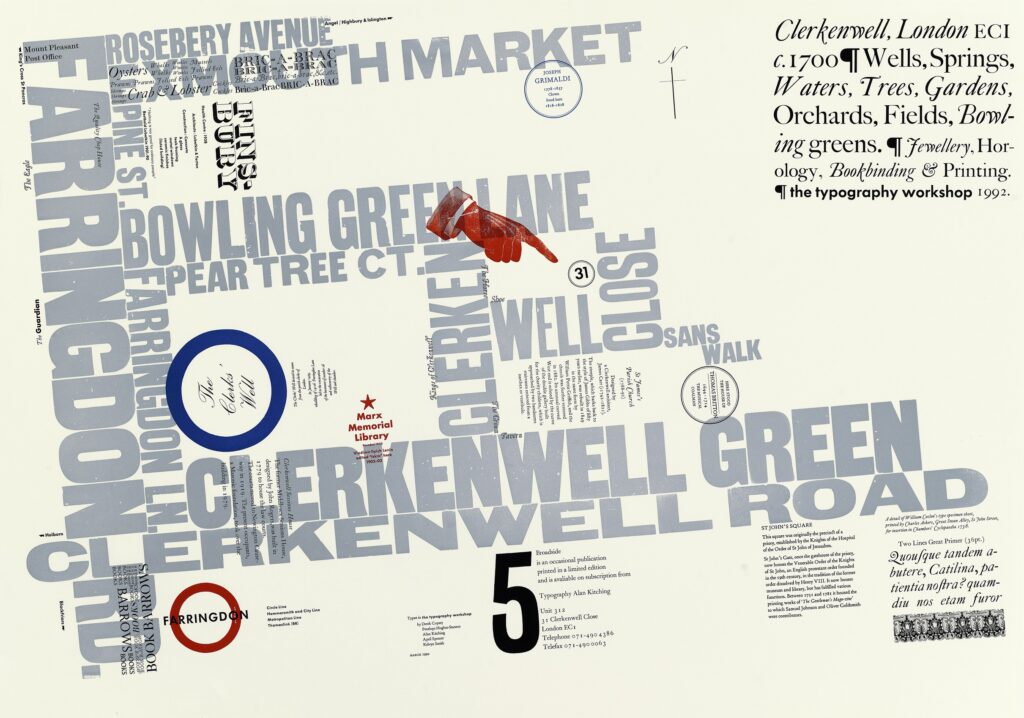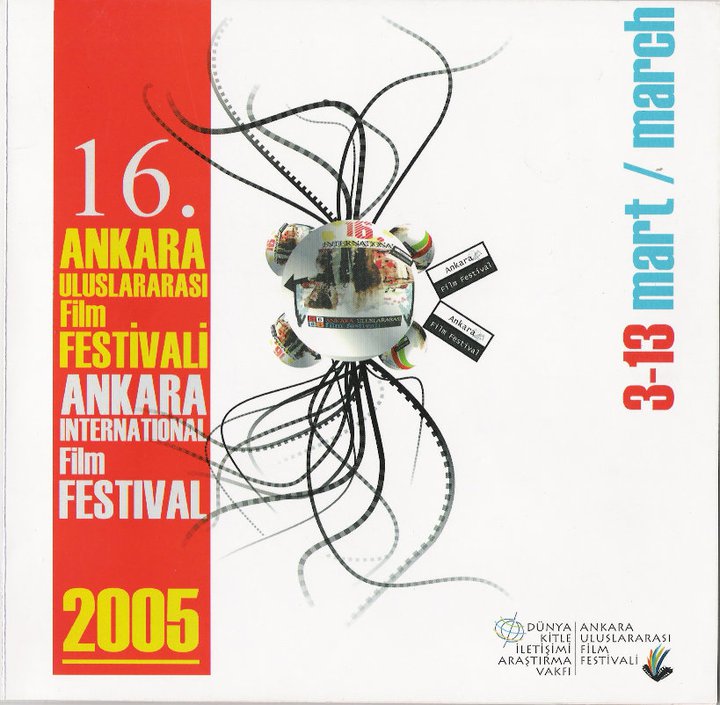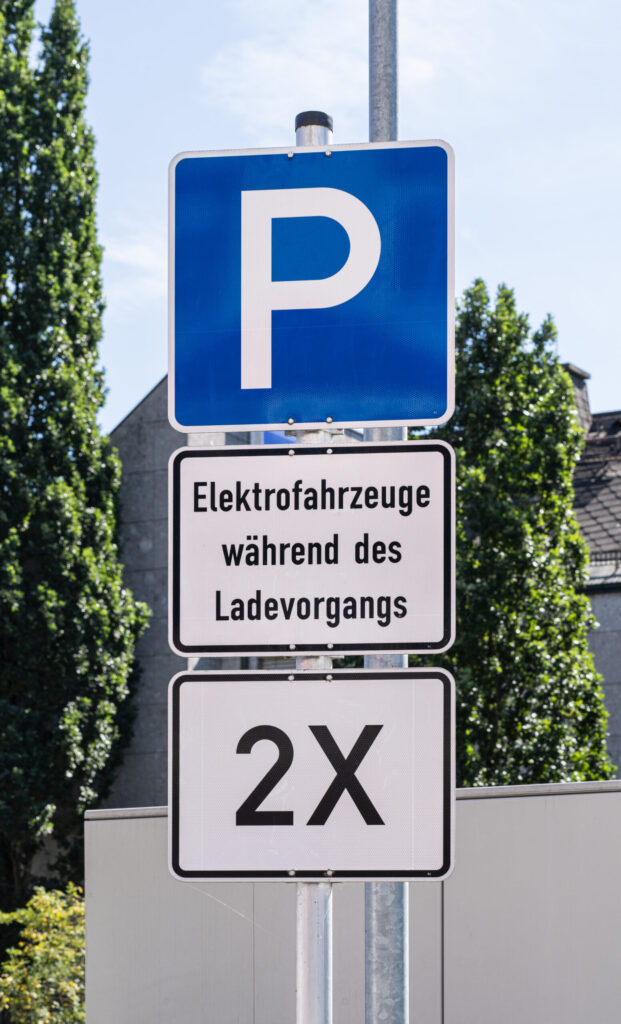
1990 bis heute
Die letzten Jahrzehnte haben einerseits eine Flut kurzlebiger Schriftentwürfe hervorgebracht, andererseits aber auch bedeutende Arbeiten renommierter Designer. Zu den prägenden Gestaltern zählen:
• Otl Aicher mit der Rotis (1988)
• Hermann Zapf mit Klassikern wie Palatino, Optima, Zapfino und ITC Zapf Dingbats
• Adrian Frutiger mit Frutiger, Univers und Avenir
• Kurt Weidemann mit der ITC Weidemann
• Werner Schneider mit der Vialog
• Erik Spiekermann mit der FF Meta, ITC Officina, FF Unit und der Berliner Grotesk
• Lucas de Groot mit Thesis, TheSans, SpiegelSans, Corpid und Mono; seine Tagesschau-Schrift gilt als erste speziell für den Bildschirm entwickelte Schrift.
Neben neuen Entwürfen spielt das Redesign klassischer Schriften eine wichtige Rolle. So modernisierte Jean-François Porchez Jan Tschicholds Sabon zur Sabon Next, indem er die Grundidee beibehielt, aber technische Einschränkungen des Bleisatzes – etwa fehlende Unterschneidungsmöglichkeiten – überwand. Viele Schriften liegen heute in unterschiedlichen Fassungen vor, die oft den Namen des Herstellers tragen, etwa Adobe Garamond oder Apple Garamond.
Pixel- und Screenfonts
Mit der Verbreitung des Internets entstehen neue Anforderungen. Schriften für Bildschirme – zunächst als Pixel- oder Screenfonts, später als optimierte Webfonts – müssen auf geringe Auflösung, unterschiedliche Displaygrößen und digitale Lesbarkeit zugeschnitten sein. Traditionelles Wissen über Lesbarkeit, Zeilenlänge und Proportionen wird dabei neu interpretiert. Heute prägen digitale Schriften das Design im Web, in Apps und Interfaces und bilden eine zentrale Säule moderner visueller Kommunikation.